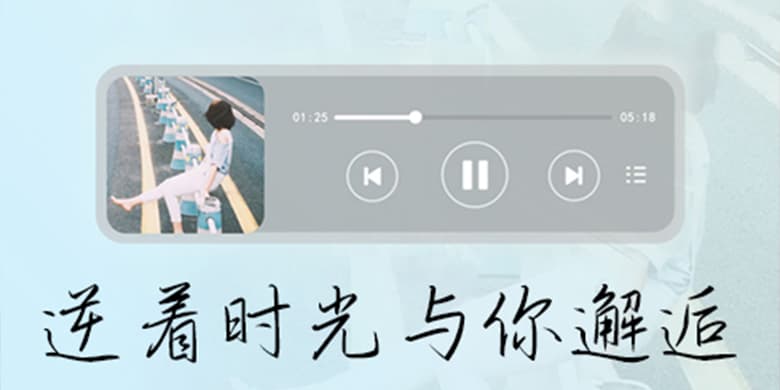
品牌:方正手迹设计师:刘殿儒发行时间:2020字库编码:大陆简体(GB2312-80)分类:常规书写·硬笔字体属性:精品字
逆着时光与你邂逅是一款优雅的手写体。该字体中宫较大,视觉上识别度较高,应用小场景不会丢失识别度。笔画延伸顺滑舒展,具有中国风的特点。该字体适用于文艺类的书刊、品牌广告和产品包装设计,以及社交网络的个性化用字。